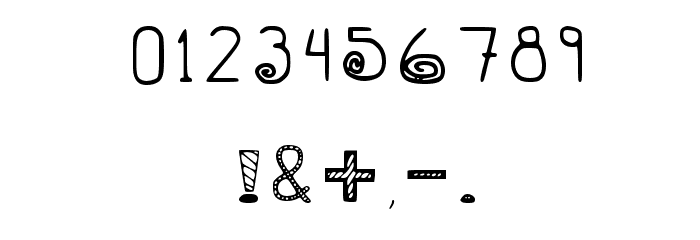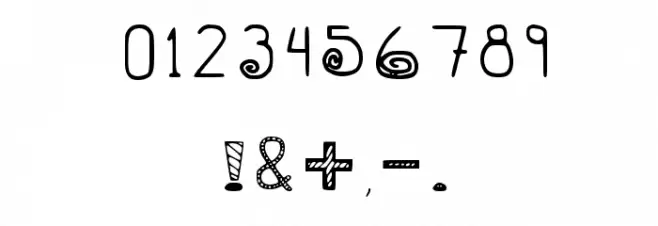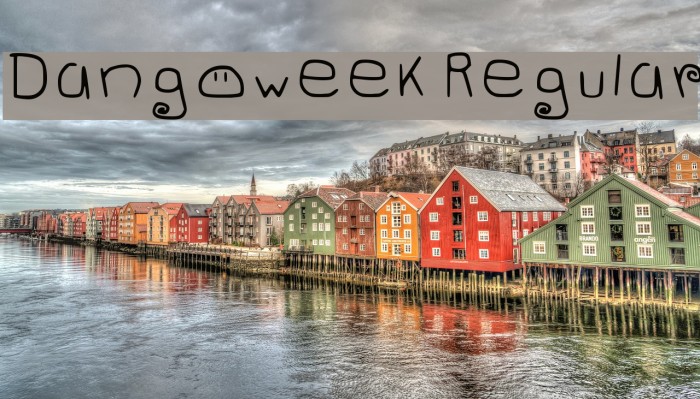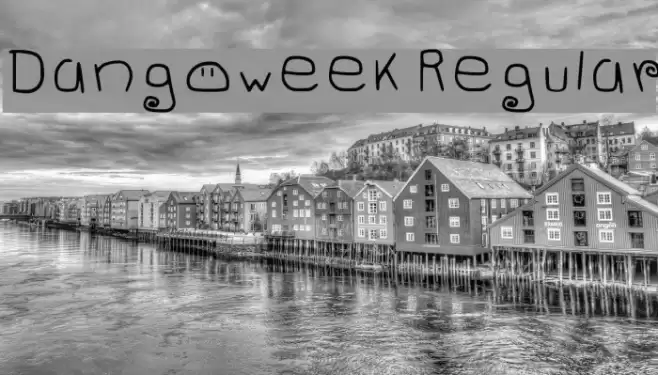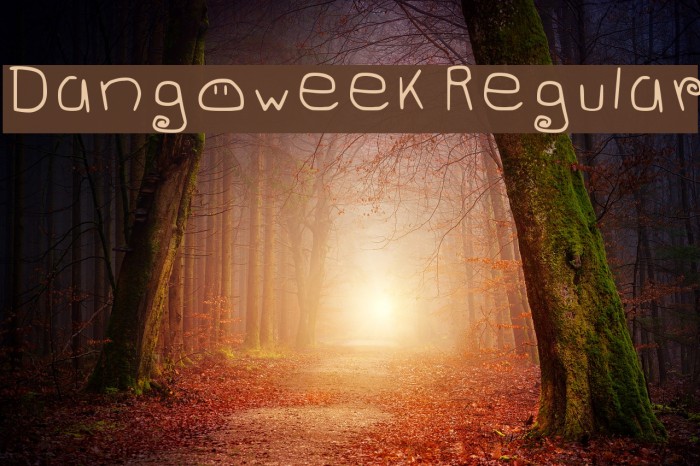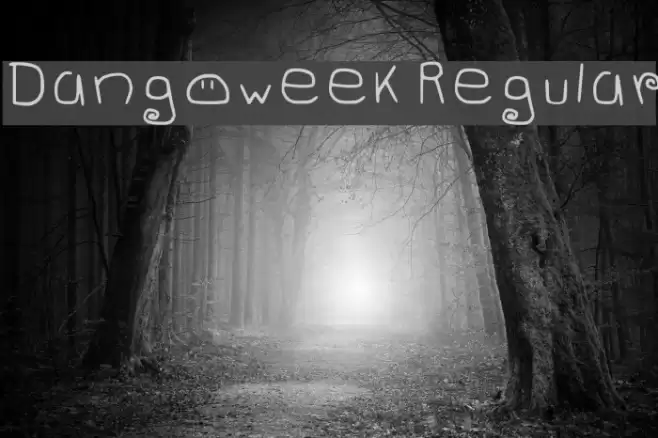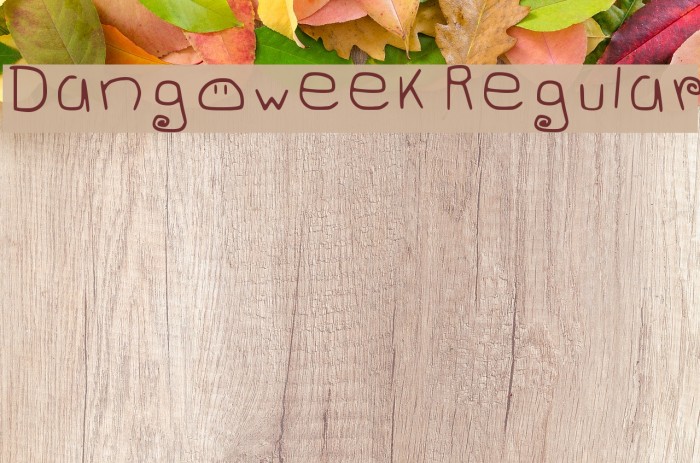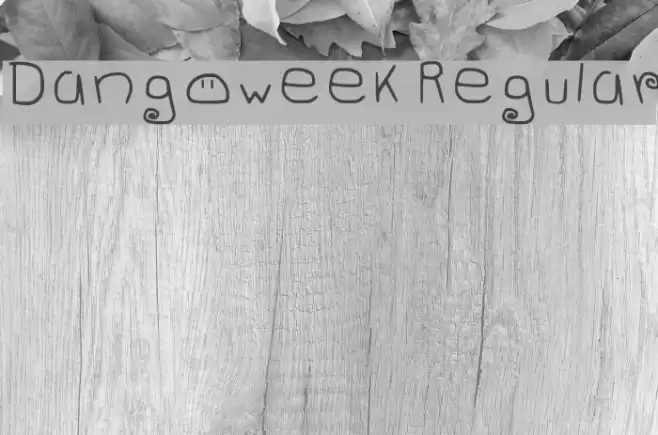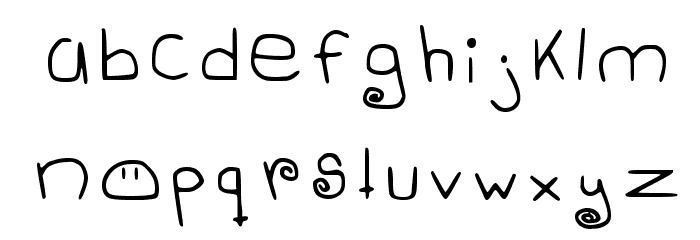
Dangoweek Regular Font
| Style général | Whimsical, Artistic |
| Cas d'utilisation | Headlines, Logos, Creative projects |
| Projets proposés | Ideal for children's books, creative posters, playful branding, and artistic invitations. |